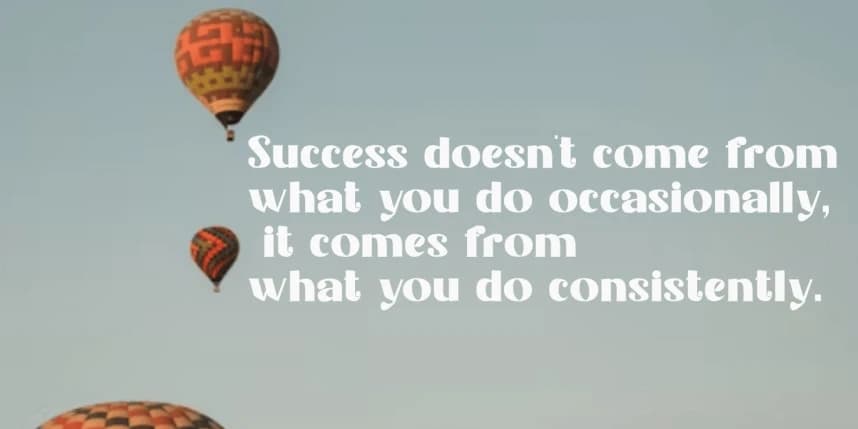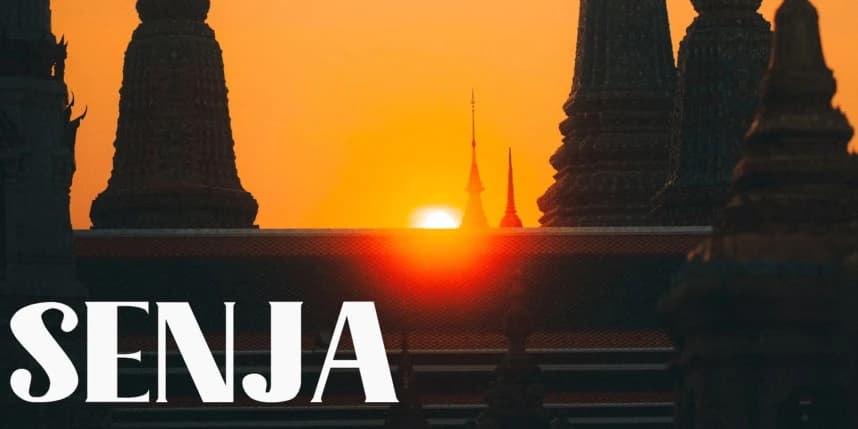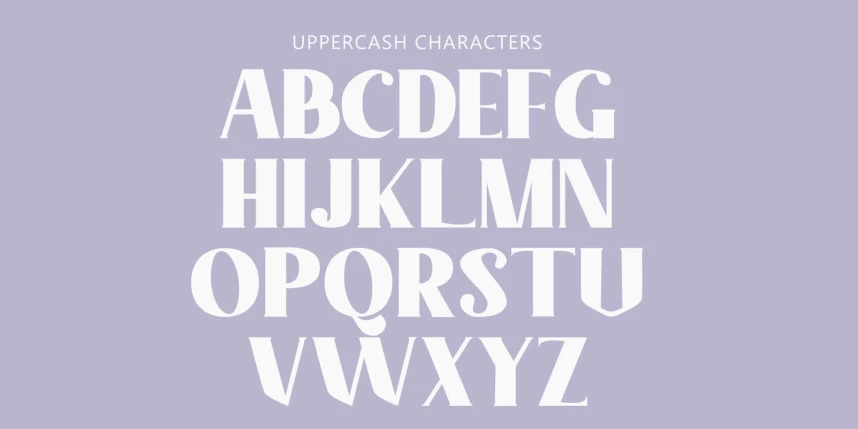
Congord Font
Congord Font, dikkat çekmek için tasarlanmış cesur bir yazı tipidir. Markalaşma, editoryal başlıklar, afişler, ambalajlar ve dikkat gerektiren her şey için mükemmel bir uyum sağlar; geometrik güç ile modern zarafeti benzersiz bir şekilde birleştirir.
Congord Font, bir ifade yaratmak için tasarlanmış cesur bir yazı tipidir. Markalaştırma, editoryal başlıklar, afişler, ambalajlar ve dikkat çekmesi gereken her şey için mükemmel derecede uygundur; Congord, geometrik güç ile modern zarafetin benzersiz bir birleşimini sunar.